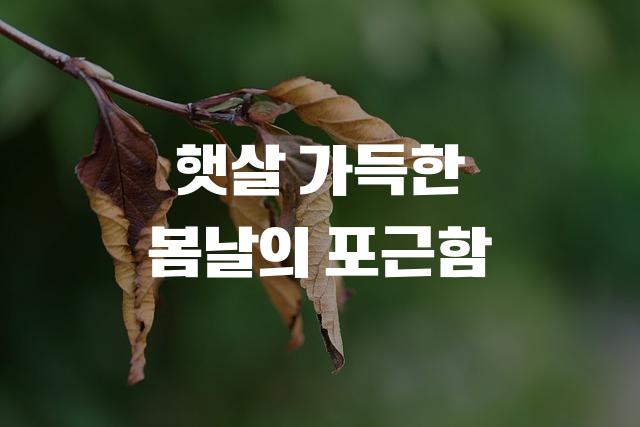
연일전통시장체
연일전통시장체는 연제구상권활성화재단에서 제작한 폰트로, 또박또박하고 어른의 손글씨 같은 감성을 담고 있습니다. 전통과 현대가 공존하는 디자인으로, 감각적이면서도 읽기 쉬운 텍스트 제공에 최적화되어 있습니다.
이 폰트의 인사이트!
친근하고 인간적인 느낌의 목소리로, 소박하면서도 따뜻한 인상을 줍니다.
연일전통시장체은(는) 손글씨, 감성적인, 부드러움 계열의 생김새를 가지고 있으며
인사말 카드, 카페 메뉴, 소셜 미디어 등에서 자주 활용되며, 효과적인 메시지 전달에 적합합니다.
이 폰트는 음식/식음료, 라이프스타일, 이벤트/웨딩 분야에 잘 어울리며,
전통적, 편안한, 클래식한 느낌을 담고 있는 것이 특징입니다.